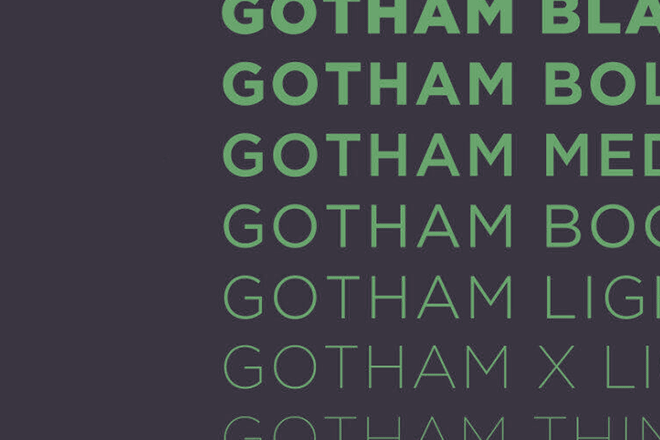
20+ Font Terbaik Mirip Gotham
Gotham adalah font yang terkenal sebagai jenis huruf modern-klasik. Meskipun relatif baru, font ini telah digunakan di banyak proyek desain bergengsi mulai dari kampanye presiden Barack Obama hingga perusahaan terkemuka seperti Taco Bell, jaringan CBN, Discovery Inc, dan banyak lagi.
Tak perlu dikatakan lagi, Gotham adalah salah satu font sans-serif geometris terbaik yang pernah ada. Sayangnya, tidak semua orang memiliki kemewahan untuk menggunakan font ini dalam desain mereka karena biaya lisensinya yang besar. Untungnya, ada solusinya.
Dalam postingan ini, kami melihat beberapa font terbaik yang mirip dengan Gotham. Font ini memiliki tampilan klasik modern yang sama dengan font Gotham dan memungkinkan Anda menggunakannya dalam proyek komersial dan klien tanpa menghabiskan seluruh anggaran Anda untuk perizinan.
Tentu saja, kami juga menyertakan beberapa font gratis. Coba lihat.
Katide
Katide adalah font variabel dengan rentang mengesankan yang menampilkan karakter lebar, yang terkenal dengan Gotham. Berbeda dengan Gotham, font Katide menawarkan lebih banyak fleksibilitas bagi Anda untuk menemukan tampilan dan gaya yang tepat untuk desain tipografi Anda, berkat format variabelnya. Font ini mencakup karakter huruf besar dan kecil dengan banyak alternatif, memungkinkan Anda bereksperimen dengan gaya yang berbeda.
Horas
Horas adalah font sans serif geometris lainnya yang hadir dengan desain huruf yang sangat bergaya. Memiliki karakter luas yang memancarkan keanggunan dan profesionalisme. Pilihan tepat untuk proyek desain bergaya minimal seperti desain branding modern, logo, dan majalah. Ini juga memiliki karakter yang jauh lebih tajam daripada Gotham dan sangat cocok untuk proyek media cetak dan digital.
Visby CF
Visby CF adalah keluarga font serbaguna yang hadir dalam delapan variasi font dan miring yang berbeda. Font ini juga dilengkapi huruf Latin dan Sirilik sehingga memberikan jangkauan yang lebih komprehensif. Jika dibandingkan dengan Gotham, Visby memiliki desain huruf yang jauh lebih bersih namun memiliki banyak kemiripan. Menurut sang desainer, font tersebut memiliki dua kepribadian— “Ramah dan karismatik dalam huruf kecil; canggih dan berwibawa dalam huruf besar.”
Proda Sans
Proda Sans adalah keluarga font serbaguna lainnya yang mencakup 18 font berbeda. Dan itu menampilkan karakter dengan tinggi x lebih tinggi yang mirip dengan Gotham. Proda adalah font bergaya humanis yang mengambil inspirasi dari desain tipografi pertengahan abad ke-20. Font ini mencakup berbagai bobot mulai dari tipis hingga hitam untuk disesuaikan dengan semua judul, judul, dan desain teks isi Anda. Ia juga dilengkapi dukungan untuk lebih dari 200 bahasa.
Sanshiro
Sanshiro adalah font sans-serif yang sangat profesional yang mampu menangani segala jenis desain tipografi untuk segala hal mulai dari kampanye iklan hingga desain branding. Ini memiliki desain huruf geometris dengan 9 bobot font dan huruf miring yang berbeda. Sanshiro memiliki beberapa kemiripan dengan Gotham tetapi lebih merupakan font yang mengambil inspirasi dari Gotham dan menambahkan keunikan tersendiri pada desain hurufnya. Dan itu berhasil!
Geordia
Geordia adalah salah satu font paling bergaya yang akan Anda temukan di daftar kami. Ini menampilkan desain huruf unik dengan tinggi x tinggi, yang tampaknya bahkan lebih tinggi daripada tinggi x karakter Gotham. Font ini menawarkan tampilan bersih dan minimalis yang sangat cocok dengan desain branding, header situs web, poster, dan banyak lagi.
HANYA Sans
Just Sans adalah keluarga font besar yang hadir dalam berbagai gaya bobot font, format, dan kumpulan karakter yang luas. Ada 7 bobot font berbeda untuk dipilih dan sebagai bonus, ini juga menyertakan font variabel. Setiap font memiliki lebih dari 620 karakter bersama dengan beberapa rangkaian gaya. Yang terpenting, font ini memiliki gaya desain yang bersih, minimal, dan geometris seperti font ikonik Gotham.
Panggung Grotesk
Dalam hal branding, logo, dan desain kemasan untuk merek modern, tampilan yang bersih dan sederhana adalah pilihan yang tepat. Stage Grotesk memiliki kombinasi ideal yang memungkinkan Anda membuat desain tipografi elegan untuk bisnis kelas atas dan mewah. Font ini memiliki desain karakter yang mirip dengan Gotham di lebih dari 600 mesin terbang. Dan hadir dalam 14 font berbeda untuk dipilih, termasuk 7 bobot font dan versi miring dari setiap bobot.
Hubhead
Hubhead bukanlah alternatif dari Gotham tetapi ia hadir dengan gaya desain huruf serupa yang memungkinkan Anda menangkap getaran modern-klasik yang sama melalui tipografi Anda. Font ini memiliki karakter bulat lembut dengan guratan geometris bersih yang menawarkan nuansa sangat estetis. Ini sempurna untuk logo, kartu nama, label, dan banyak lagi. Font ini memiliki lebih dari 270 mesin terbang dan banyak alternatif juga.
Penglihatan
Vision adalah alternatif gratis yang bagus untuk font Gotham. Ini memiliki desain karakter yang bersih dengan tinggi x-tinggi, mirip dengan Gotham. Namun karakternya tidak seluas itu. Font ini sepenuhnya gratis untuk digunakan dengan proyek komersial.